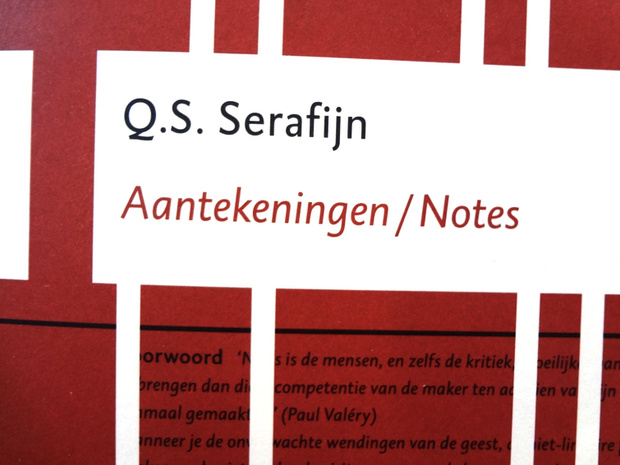
namenlose schoenheit
noch schöner wäre es, wenn ij eine ligatur wäre. und als solche vielleicht sogar noch einen verbund mit dem f einginge...
phoibos: das ist mein neuestes self-initiated projekt– nennt sich trigatur und stellt den verbund von drei lettern.
würd ich trotzdem spektakulärer erwarten, insbesondere bei der dutch type library...